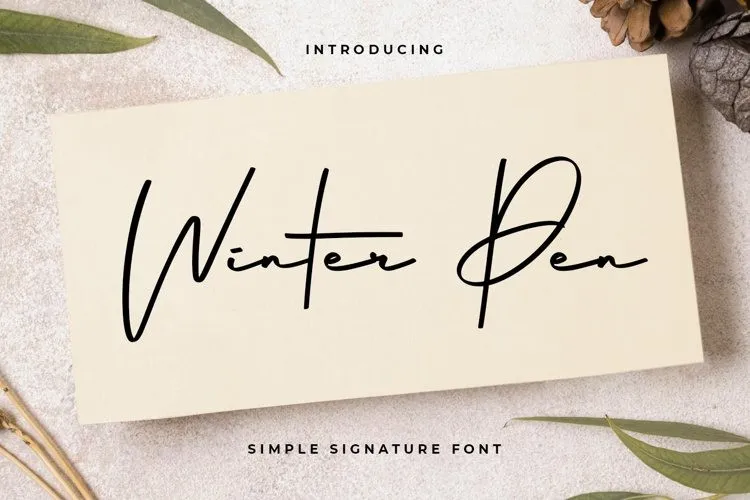
A fonte Winter Pen é perfeita para aqueles que buscam um estilo elegante e distintivo, oferecendo uma opção única para criar designs memoráveis. Especialmente criada pelos talentosos designers da 99designs, essa fonte Script é feita para trazer seu trabalho à vida, fazendo-o ficar de fora do normal. Desenvolvida cuidadosamente por Abodaniel, ela se adapta a várias ideias e pode transformar qualquer criação em algo realmente impressionante. Com seu estilo distintivo e duradouro, você sentirá uma verdadeira paixão pela fonte Winter Pen, apreciando sua elegância e sofisticação. Seja para assinaturas, materiais de publicação ou até mesmo design gráfico, esta fonte trará seu trabalho a um novo nível de perfeição. Transforme seus projetos com essa fonte e faça-os brilhar de uma maneira única.